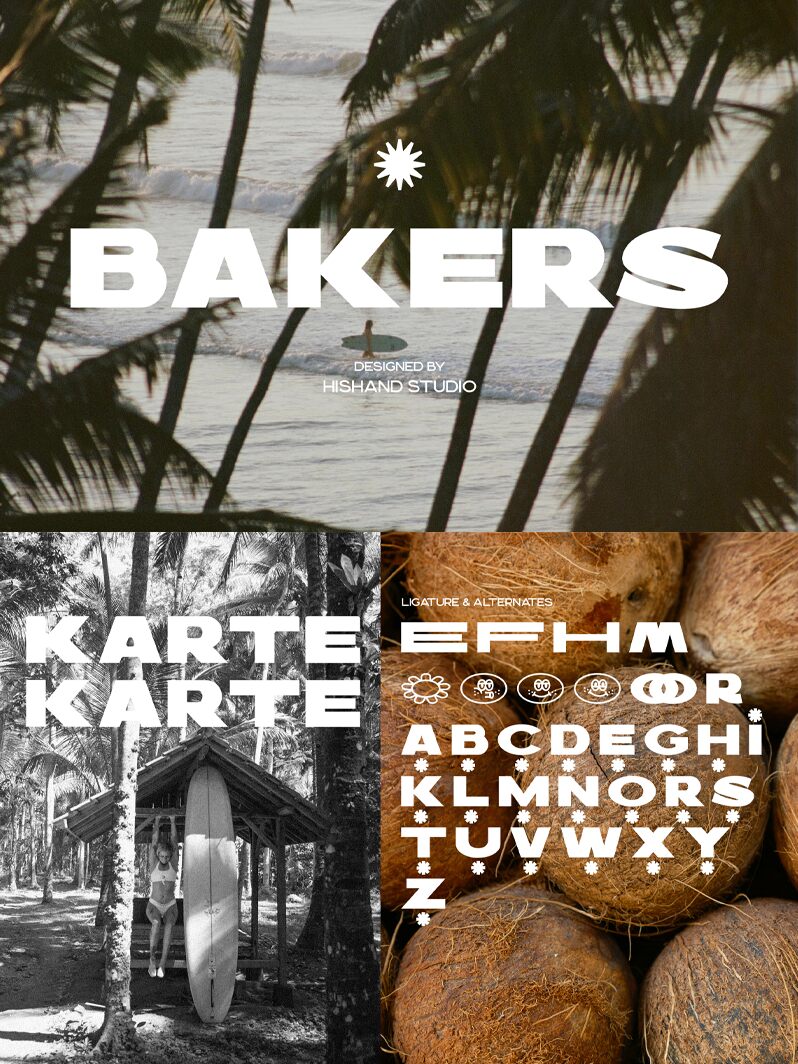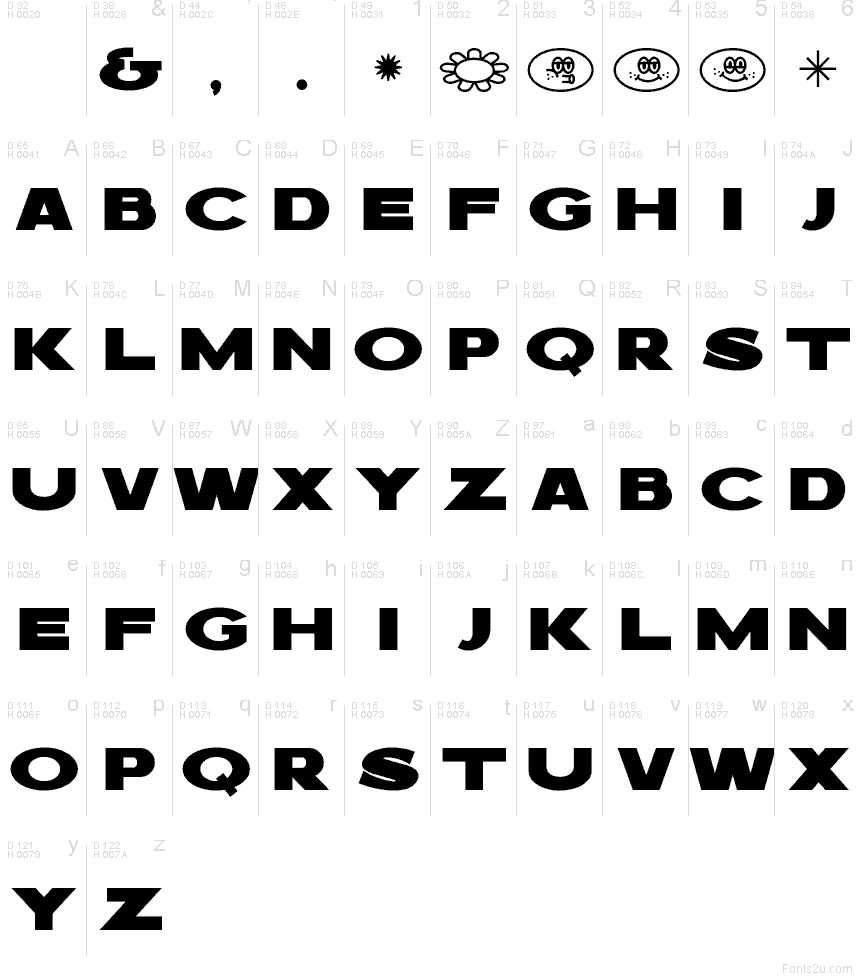
Bakers od Hishand Studio to darmowy, industrialny bezszeryfowy krój pisma, zbudowany na bazie masywnych wielkich liter i ostrej, plakatowej estetyki. Litery wyglądają, jakby zostały wycięte z solidnych brył, z szerokimi skosami i powtarzalnym systemem poziomych nacięć, które nadają fontowi twardy, markowy rytm.
Świetnie sprawdza się w projektach opakowań, logotypach piekarni, szyldach, plakatach imprezowych, nagłówkach menu i krótkich tytułach, gdzie ta masywna, surowa tekstura może nieść cały komunikat. Jako darmowy font, Bakers sprawdza się również w kartach tytułowych, monogramach i wyrazistych grafikach do mediów społecznościowych – zwłaszcza gdy chcesz, aby kilka słów wyglądało jak pieczątka, wypieczony napis i było jednoznacznie graficzne.